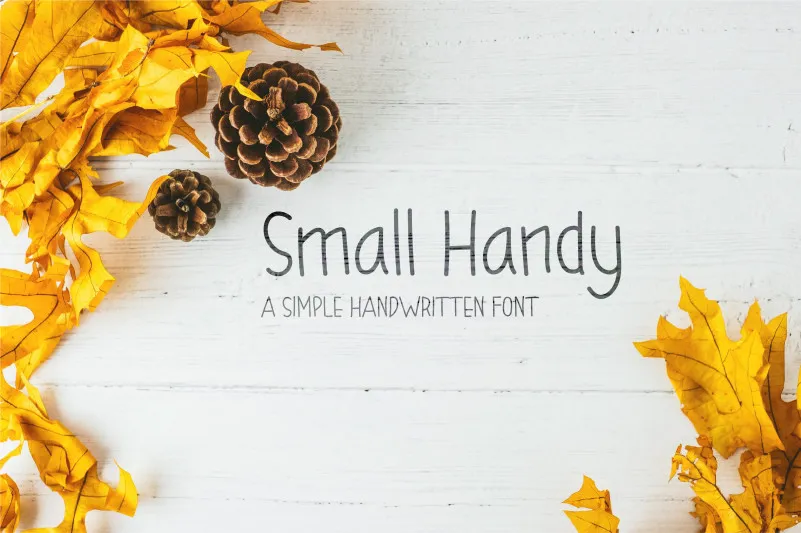
Small Handy Font – Download Grátis
Esta é uma fonte feita à mão que transmite simplicidade e minimalismo, perfeita para criar logomarcas impactantes, estilos de marca distintivos e frases inspiradoras. Suavemente elegante e versátil, ela é ideal para quem busca personalizar seus projetos com um toque autêntico e inovador. Adorarão sua capacidade de se adaptar a uma variedade imensa de formatos, tornando-a perfeita para aplicação em qualquer tipo de design. Aqui está o seu momento para criar designs memoráveis e únicos, usando este Small Handy Font que transformará suas ideias em obras de arte.
Designer: salamahstudio